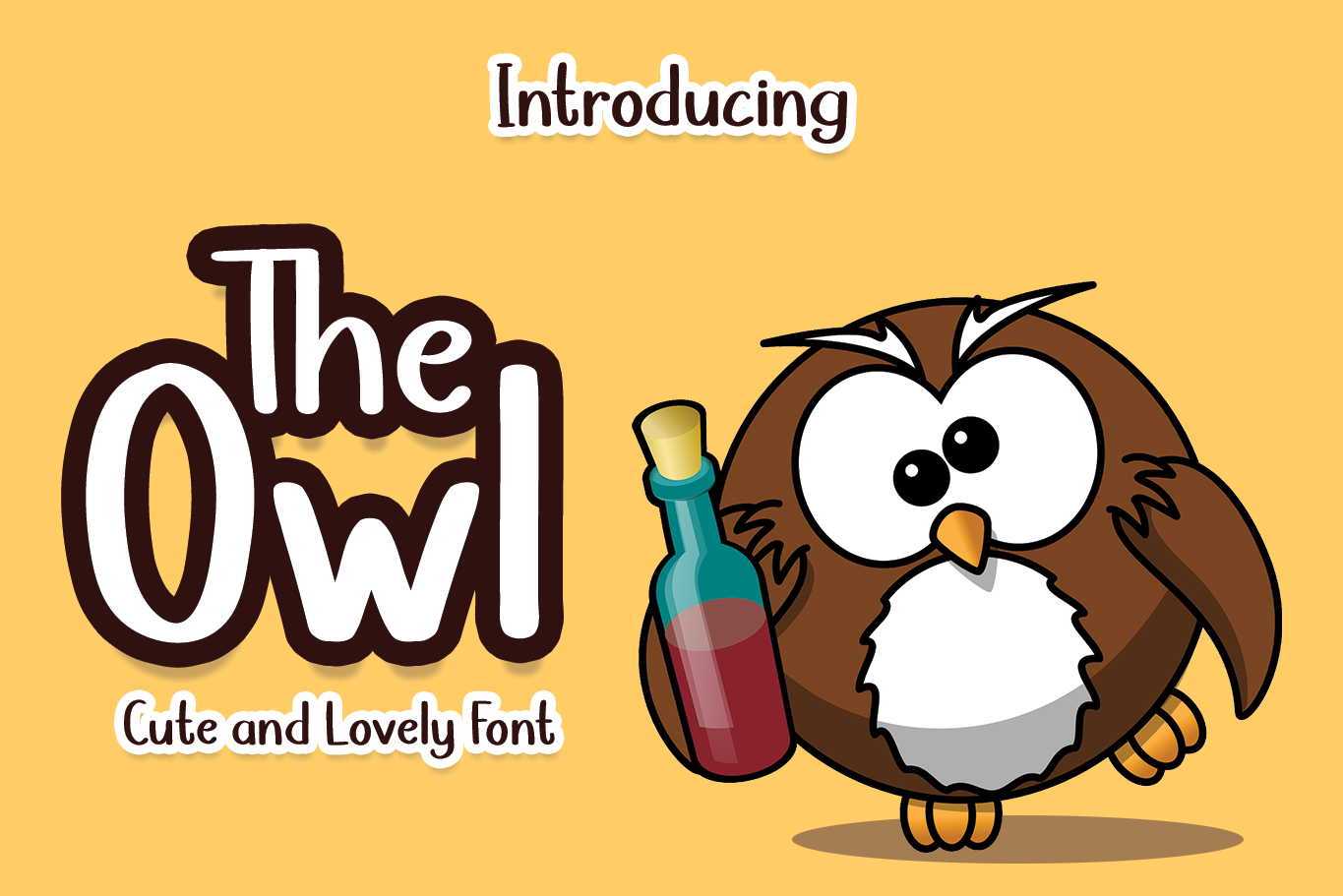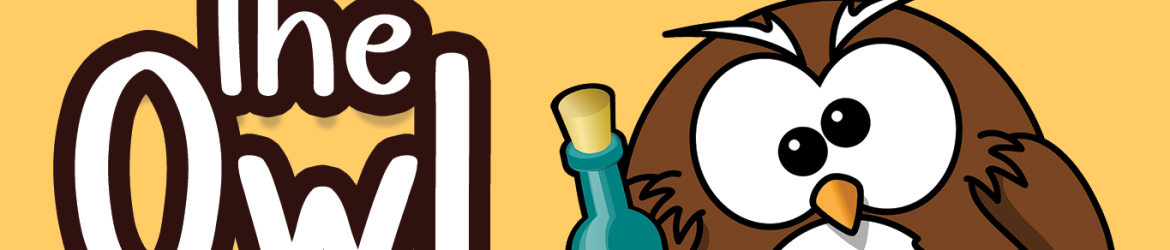
A fonte The Owl Font é ideal para aqueles que buscam uma opção divertida e animada para seus projetos visuais. Com personagens amigáveis e uma aparência levemente legível, esta fonte display se destaca não apenas como uma escolha versátil, mas também como uma ótima opção para um grande range de aplicativos. Seja em livros, revistas ou roupas, banners e muito mais, The Owl Font tem o poder de transformar qualquer projeto em um visual atrativo e único. Essa fonte é perfeita para designers que desejam dar uma pitada de diversão às suas criações, sem comprometer a legibilidade e o design elegante que tanto valorizamos na nossa identidade visual. Sem dúvida, The Owl Font não apenas oferece uma maneira divertida de expressar seu estilo pessoal em projetos visuais, mas também expande as possibilidades criativas do designer.